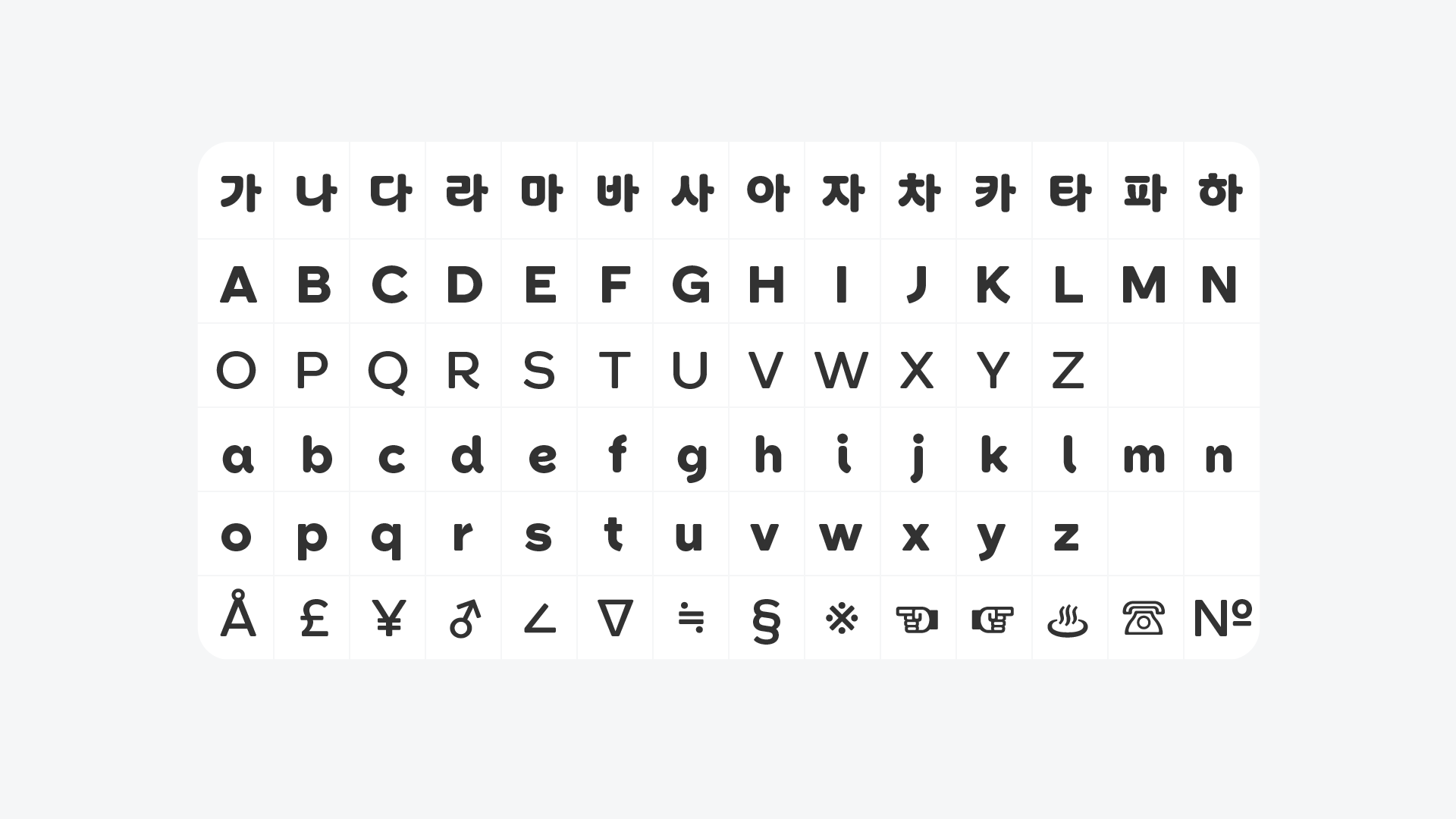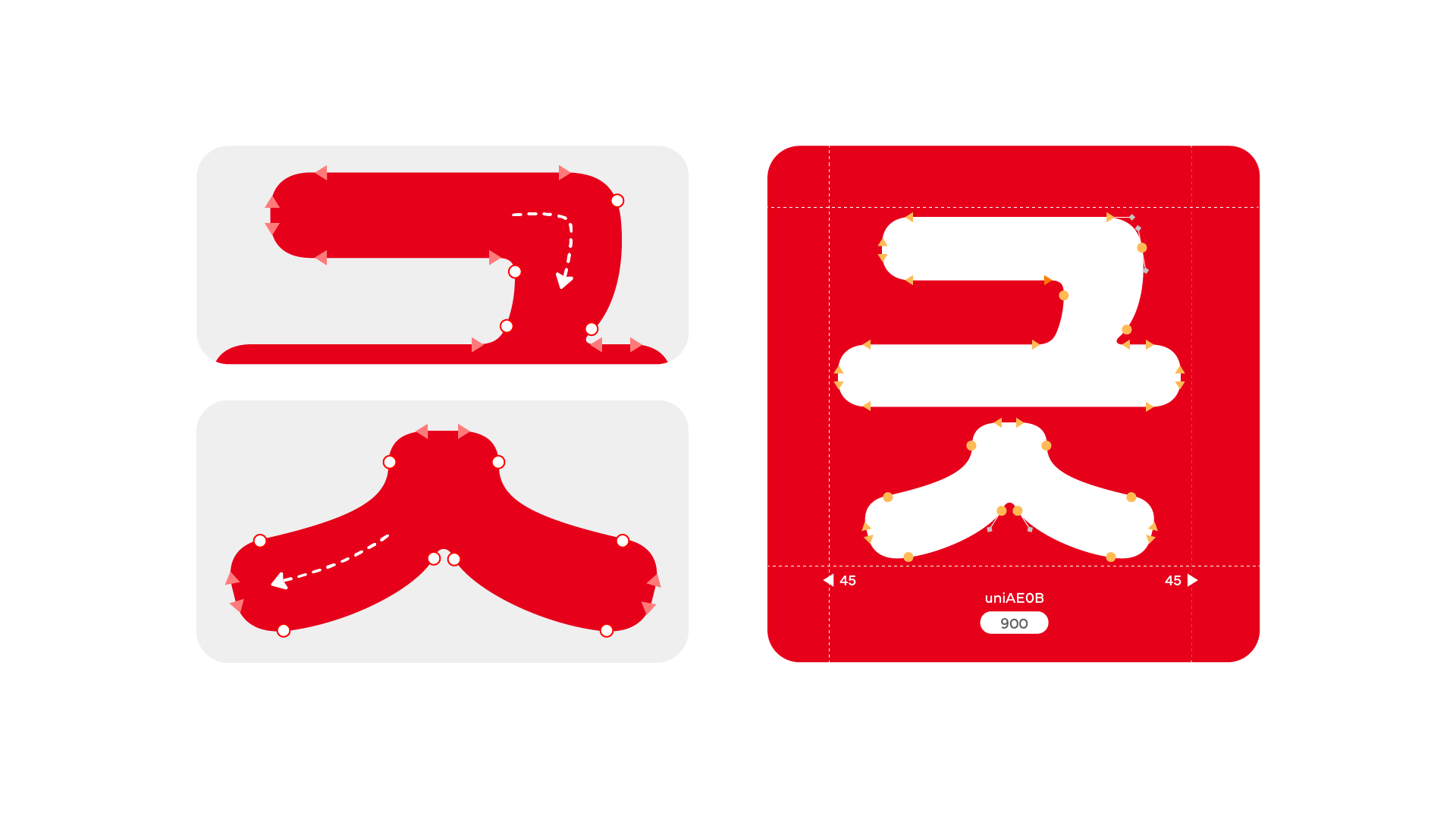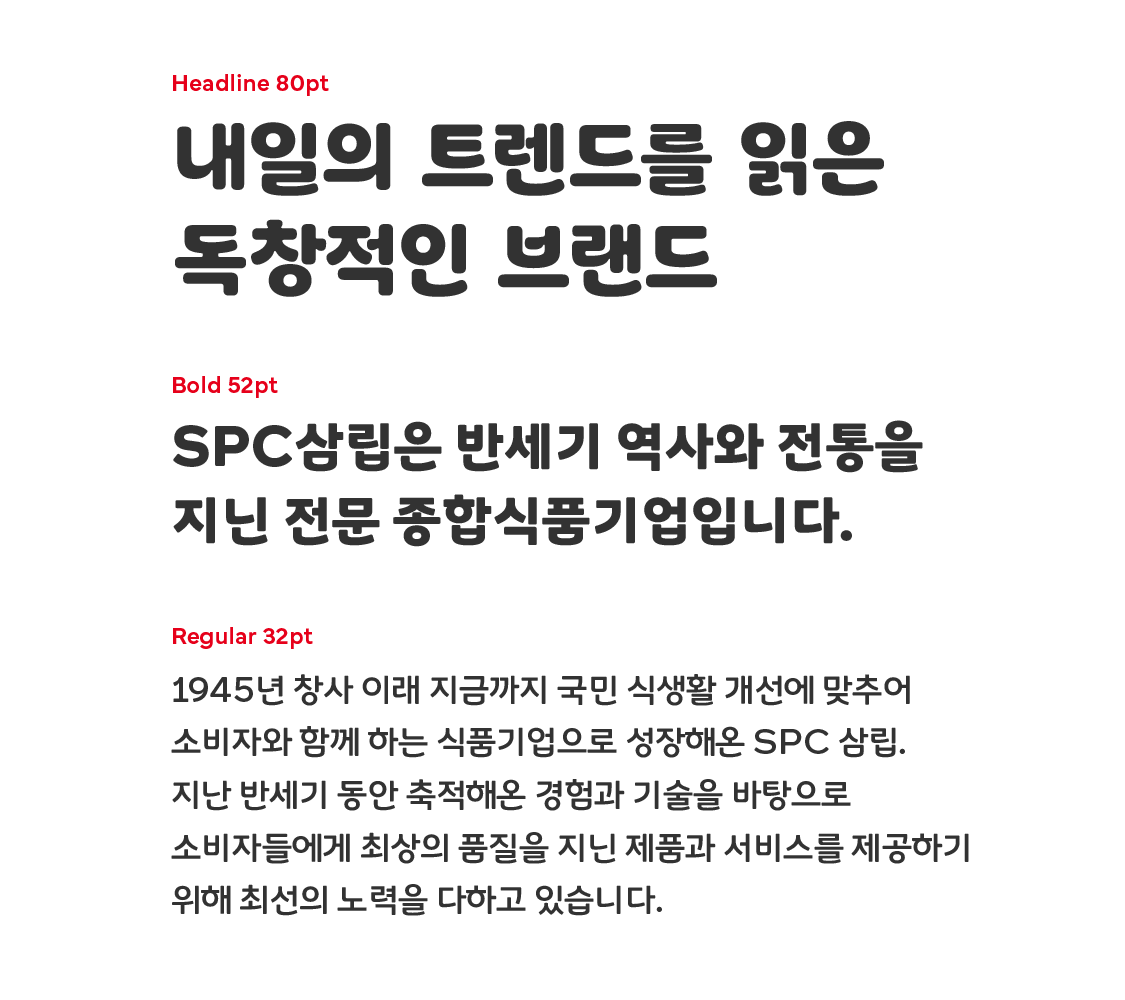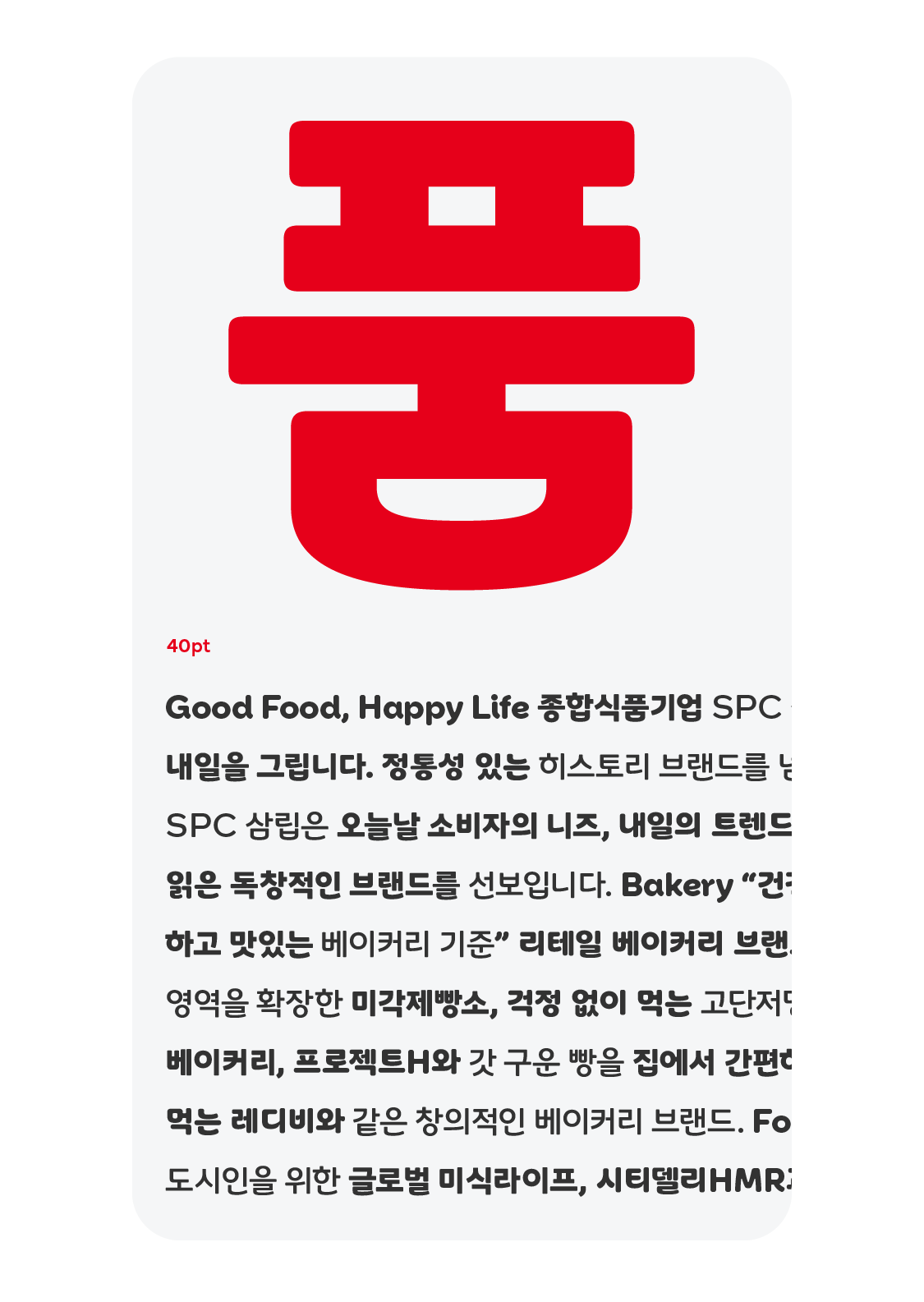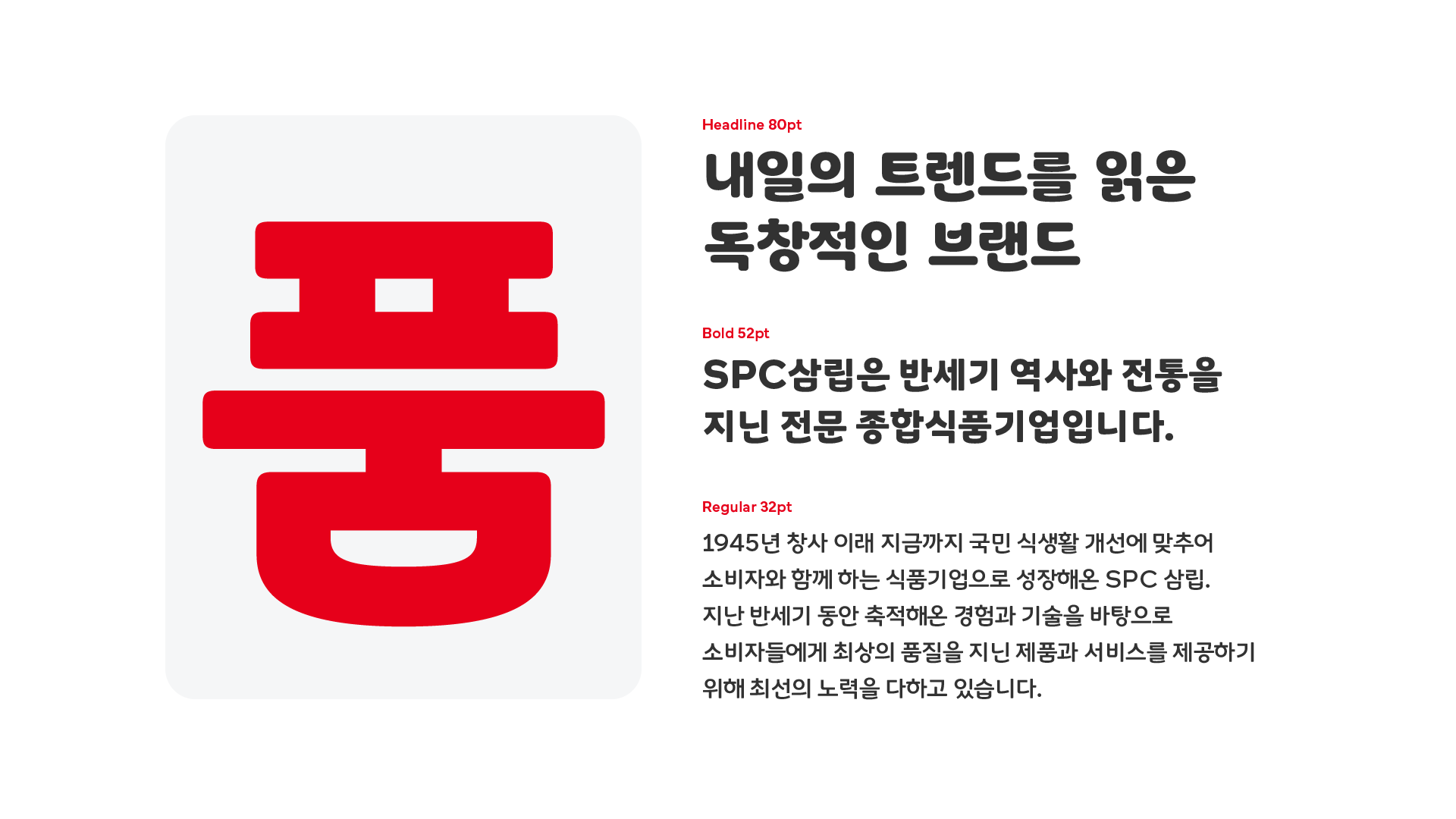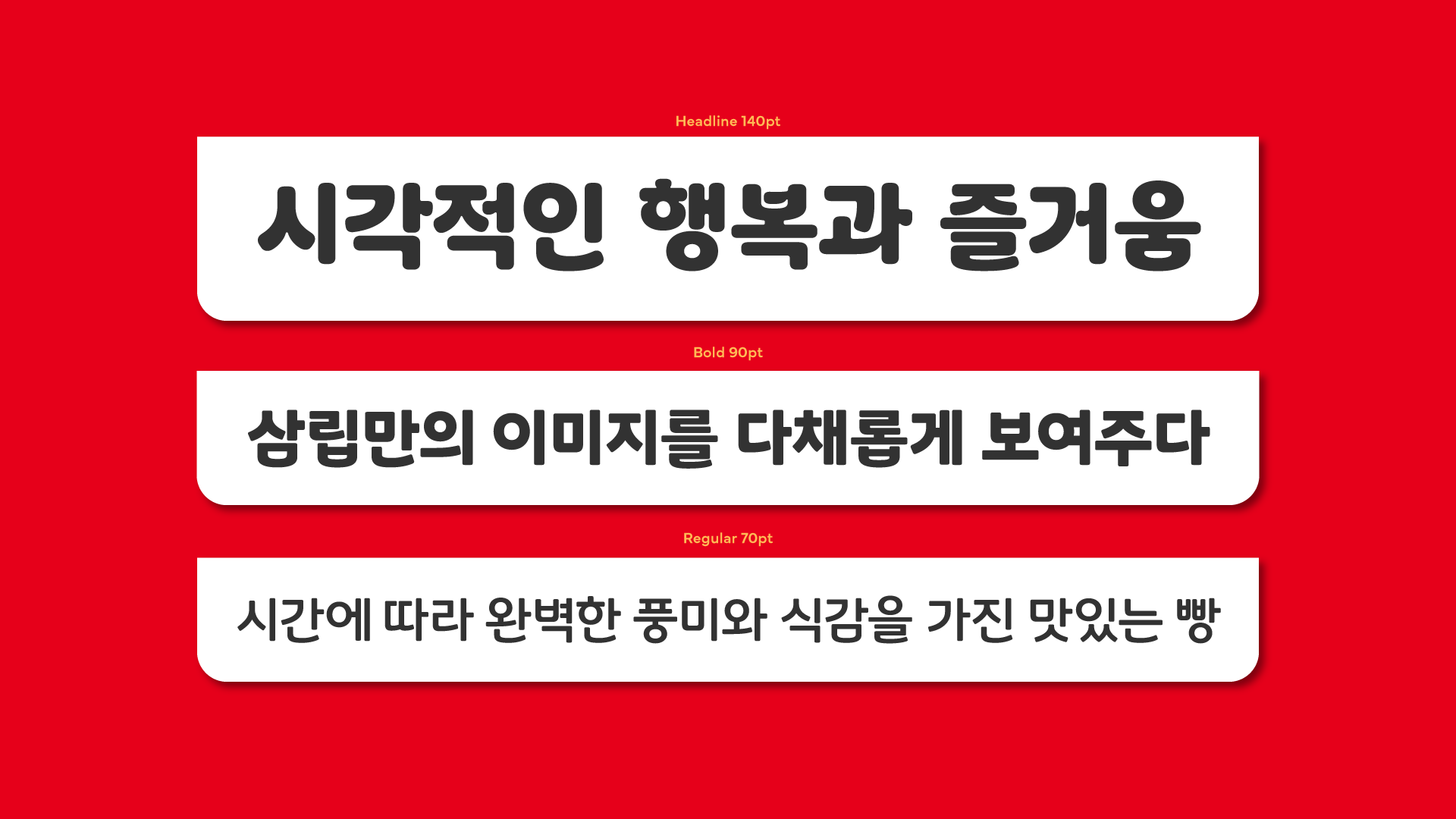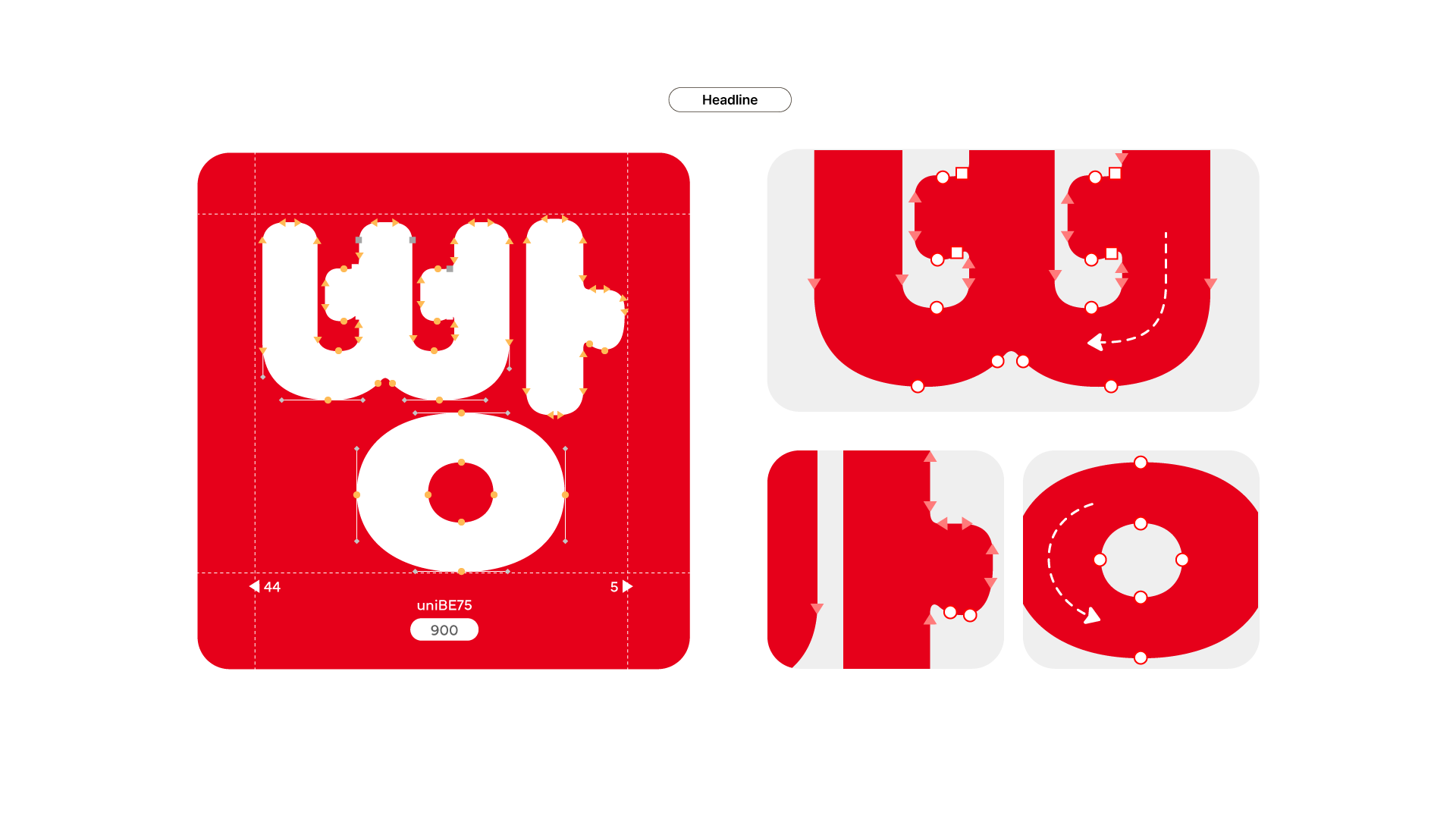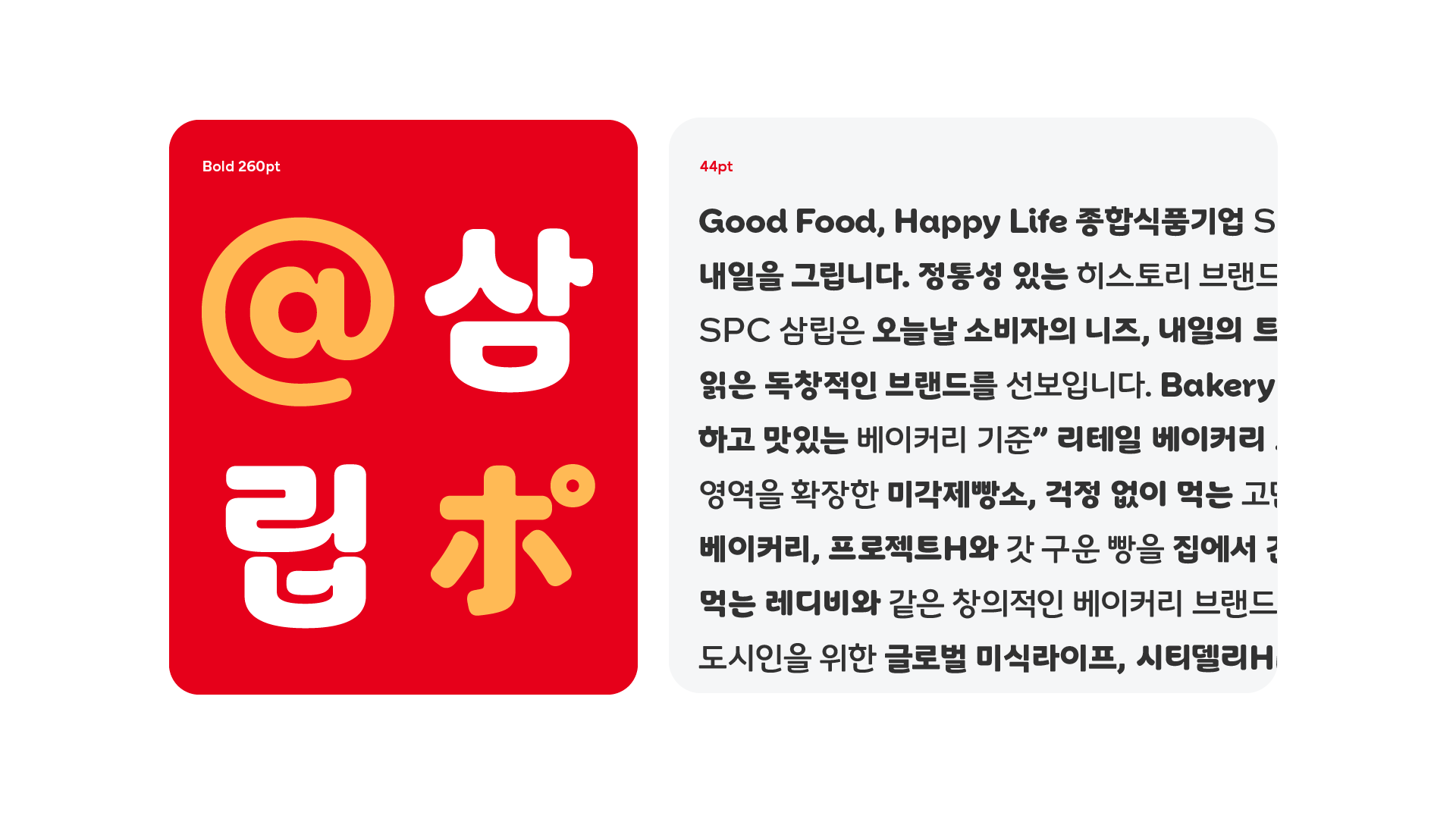
Regular / Bold
같은 재료를 사용하여도 최적의 발효 온도와 시간에 따라 완벽한 풍미와 식감을 가진 맛있는 빵이 나오듯, 본문용 서체는 ‘상미당 정신’이 재료가 되어 삼립만의 스토리를 담고 쓰임새를 최우선으로 고려하여 최적의 서체로 제작합니다. 이러한 과정으로 제작된 삼립의 서체는 사용되는 과정이나 매체에 제약없이 삼립의 색이 담겨있는 삼립만의 이미지를 다채롭게 보여줍니다.
Headline
최적의 온도와 시간으로 하여금 온전하게 발효되어 오븐에 구웠을 때 비로소 잘 구워진 맛있는 빵이 됩니다. 이러한 빵이 소비자에게 행복과 즐거움을 선사하듯, 제목용 서체는 완벽한 반죽과 최적의 발효 과정을 거쳐 맛있게 만들어진 삼립만의 서체로 시각적인 행복과 즐거움을 선사합니다.
Regualr / Bold
Headline
같은 재료를 사용하여도 최적의 발효 온도와 시간에 따라 완벽한 풍미와 식감을 가진 맛있는 빵이 나오듯, 본문용 서체는
‘상미당 정신’이 재료가 되어 삼립만의 스토리를 담고 쓰임새를 최우선으로 고려하여 최적의 서체로 제작하였습니다. 이러한 과정으로 제작된 삼립의 서체는 사용되는 과정이나 매체에 제약없이 삼립의 색이 담겨있는 삼립만의 이미지를 다채롭게 보여줍니다.
최적의 온도와 시간으로 하여금 온전하게 발효되어 오븐에 구웠을 때 비로소 잘 구워진 맛있는 빵이 됩니다.
이러한 빵이 소비자에게 행복과 즐거움을 선사하듯, 제목용 서체는 완벽한 반죽과 최적의 발효 과정을 거쳐 맛있게 만들어진 삼립만의 서체로 시각적인 행복과 즐거움을 선사합니다.
서체 이름
서체 종수
글자수
출시년도
삼립 빵긋체
3종 (Regular, Bold, Headline)
한글 2,780자, 영문 Basic Latin 95자, KS심볼 986자
2024